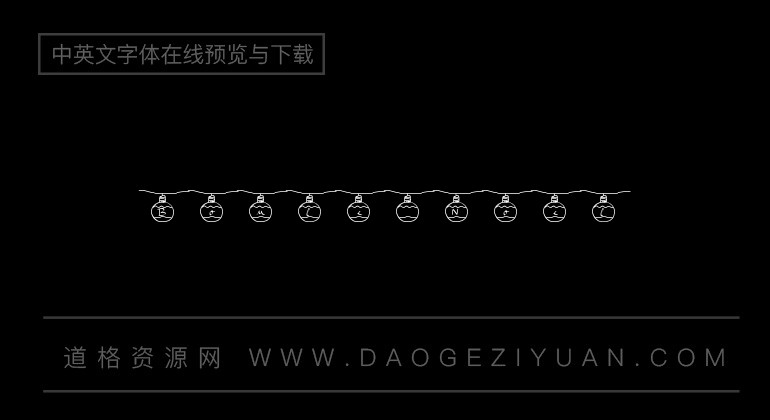
Boule Noel
Boule Noel字体是一种圆润、充满活力的手写字体,通常用于与圣诞节相关的设计项目中。这种字体的特点是每个字母都有一个圆形的轮廓,看起来像是吹气球的形状。这种字体的颜色通常是红色或绿色,这与圣诞节的颜色主题相吻合。Boule Noel字体看起来很有趣,非常适合用于制作节日贺卡、海报、宣传册和其他相关的设计项目。
Boule Noel是一款非常不错的手写艺术字体,具有很好的视觉感,适合于文化类的宣传设计、商业类品牌的广告和产品包装设计以及个性化文字排版等较多场景。